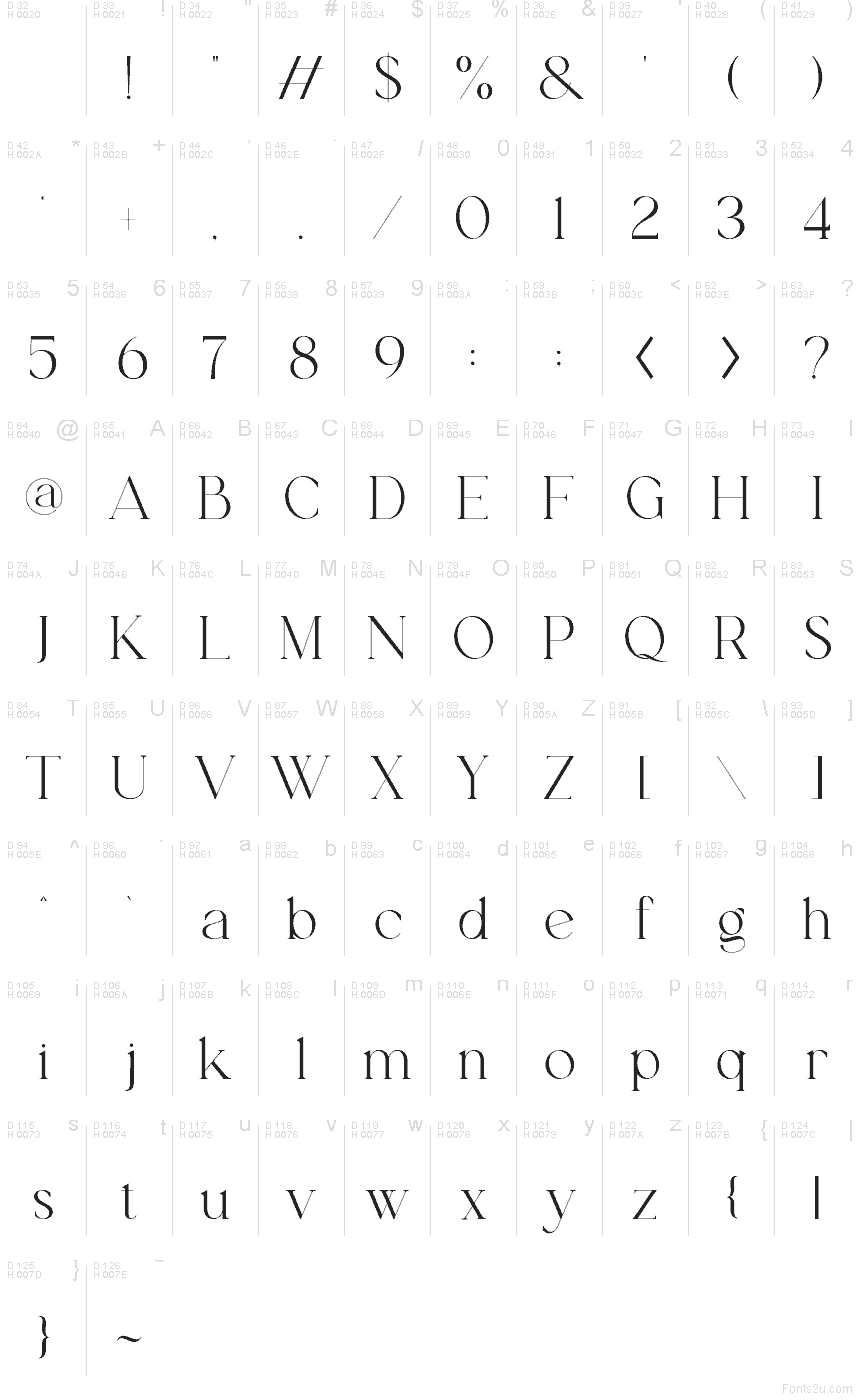
Metore Avealin, da Ermedia Studio, é uma fonte com serifa gratuita e de alto contraste, com uma postura elegante inspirada nos editoriais de moda. Suas letras alongadas combinam curvas amplas e fluidas com barras tão finas quanto agulhas e serifas retas e delicadas, criando uma silhueta leve e dramática.
Ideal para cabeçalhos e títulos refinados, ela se adapta muito bem a revistas de moda, marcas de luxo, embalagens de perfumes e convites para eventos formais, pois suas variações extremas de espessura de traço remetem às letras usadas na alta-costura e em campanhas de beleza. As curvas marcantes e os traços capilares ultrafinos podem transformar o nome de um produto em um emblema que reflete os contornos elegantes de frascos, dobras de tecidos ou fotos de joias.